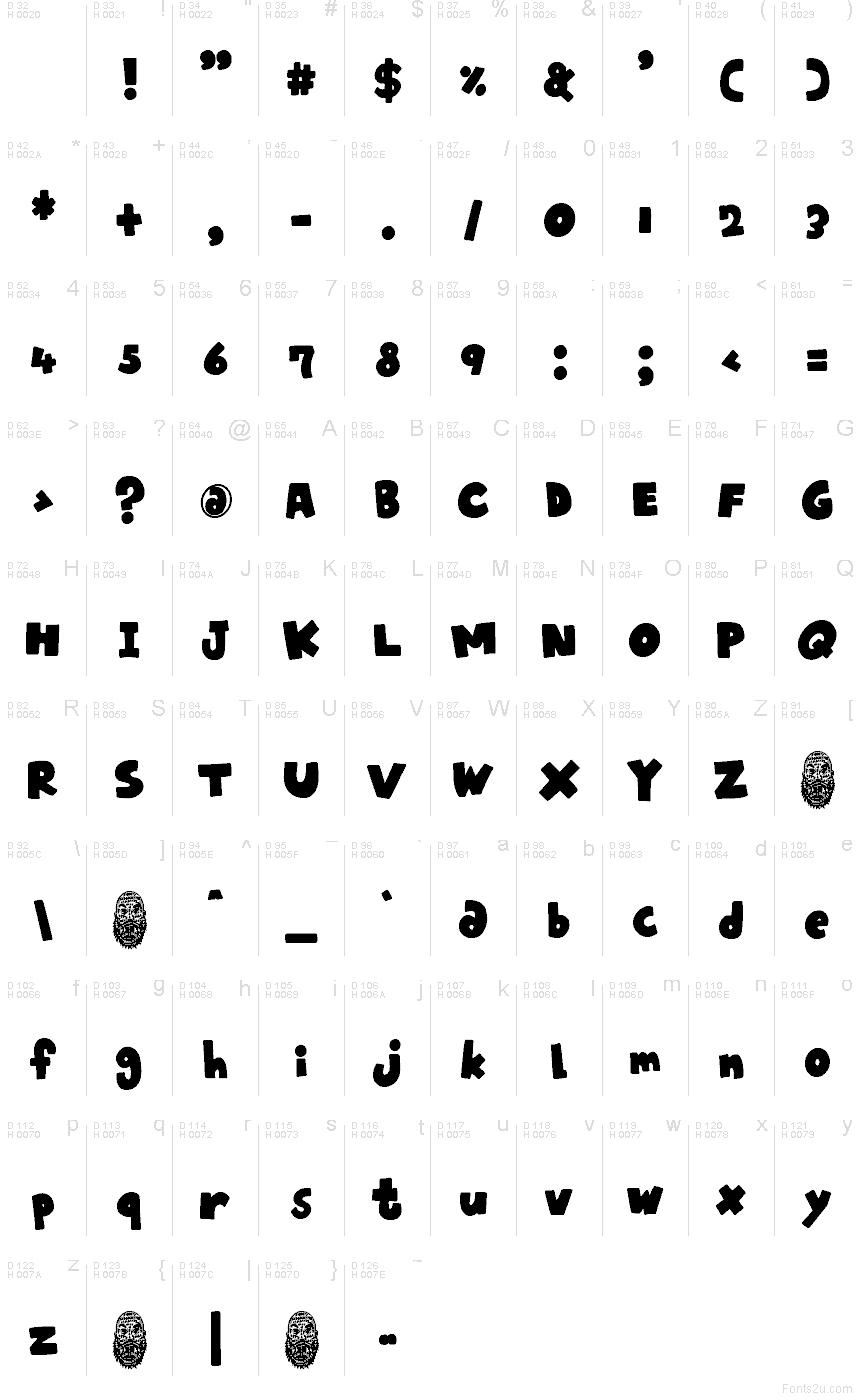
Saigon Melon
Saigon Melon von Woodcutter Manero ist eine kostenlose Cartoon-Display-Schrift mit einem weichen, voluminösen Rhythmus und einem verspielten Pop-Flair der 1970er Jahre. Die Buchstaben wirken dick und schwungvoll, mit abgerundeten Ecken, tropfenförmigen Verbindungen und schweren Formen, die das gesamte Alphabet eher weich und knautschig als geometrisch erscheinen lassen.
Sie passt perfekt auf Snack-Verpackungen, Plakate für Kinderveranstaltungen, comicartige Überschriften, Aufkleber-Designs und fröhliche Social-Media-Beiträge, bei denen ein kostenloser Font eine große, freundliche Stimme braucht. Dank der bauchigen und kompakten Formen eignet sich die Schrift auch hervorragend für kurze Titelkarten, Cover-Zeilen und logotypische Wortmarken, die einen ungezwungenen, handgezeichneten Look erfordern.